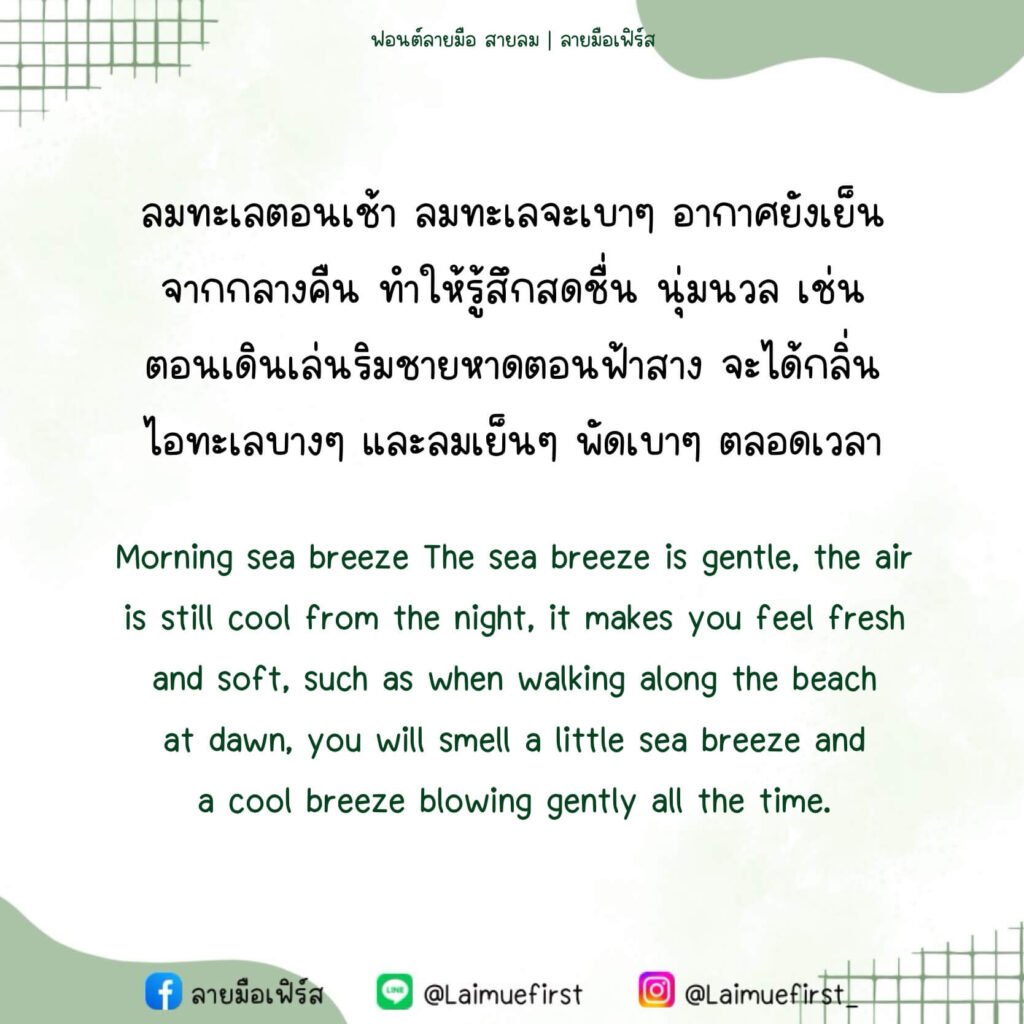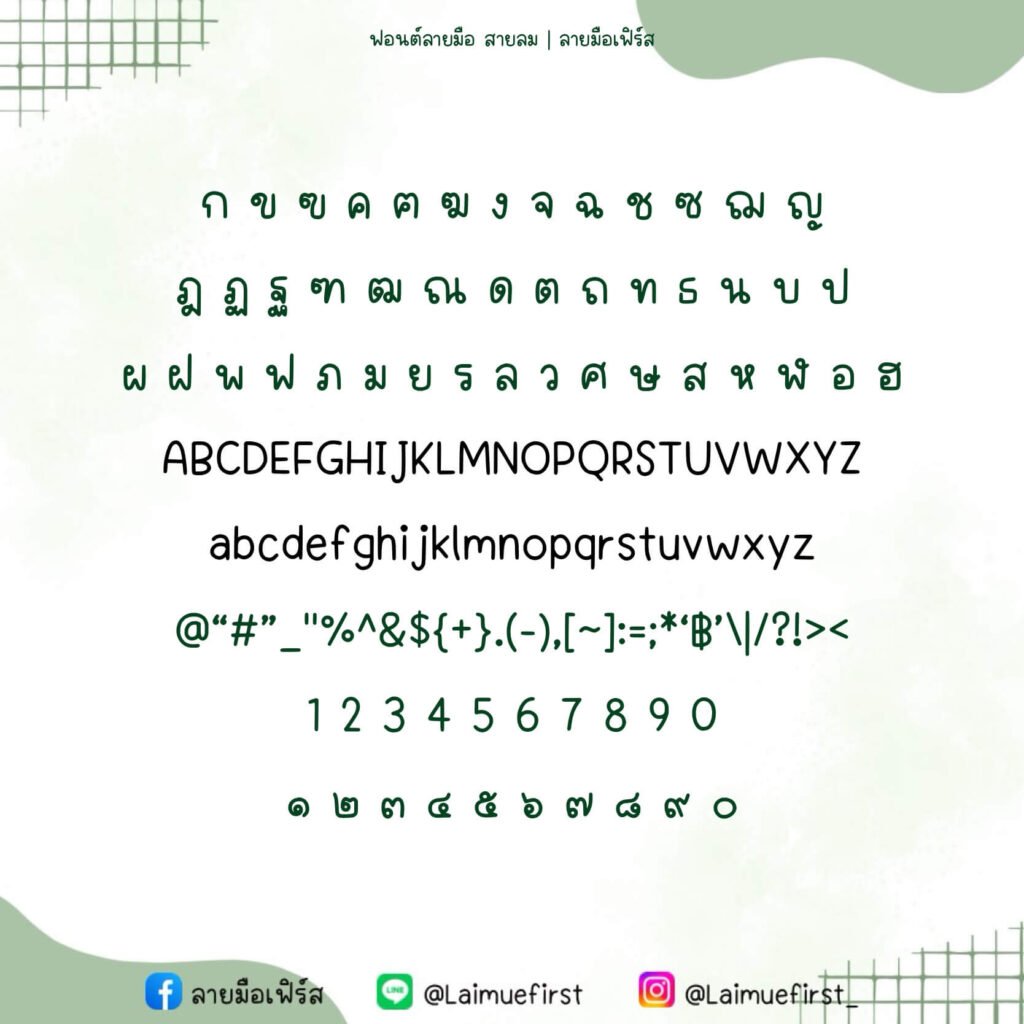
สายลม (Sailom)
ฟอนต์ลายมือ สายลม (Sailom) แจกฟรี สำหรับทดลองใช้งานแบบส่วนตัว เวอร์ชันทดลอง
เวอร์ชันทดลองใช้งาน (Demo) ตัวอักษรจะมีขนาดหนา-บางไม่เท่ากัน